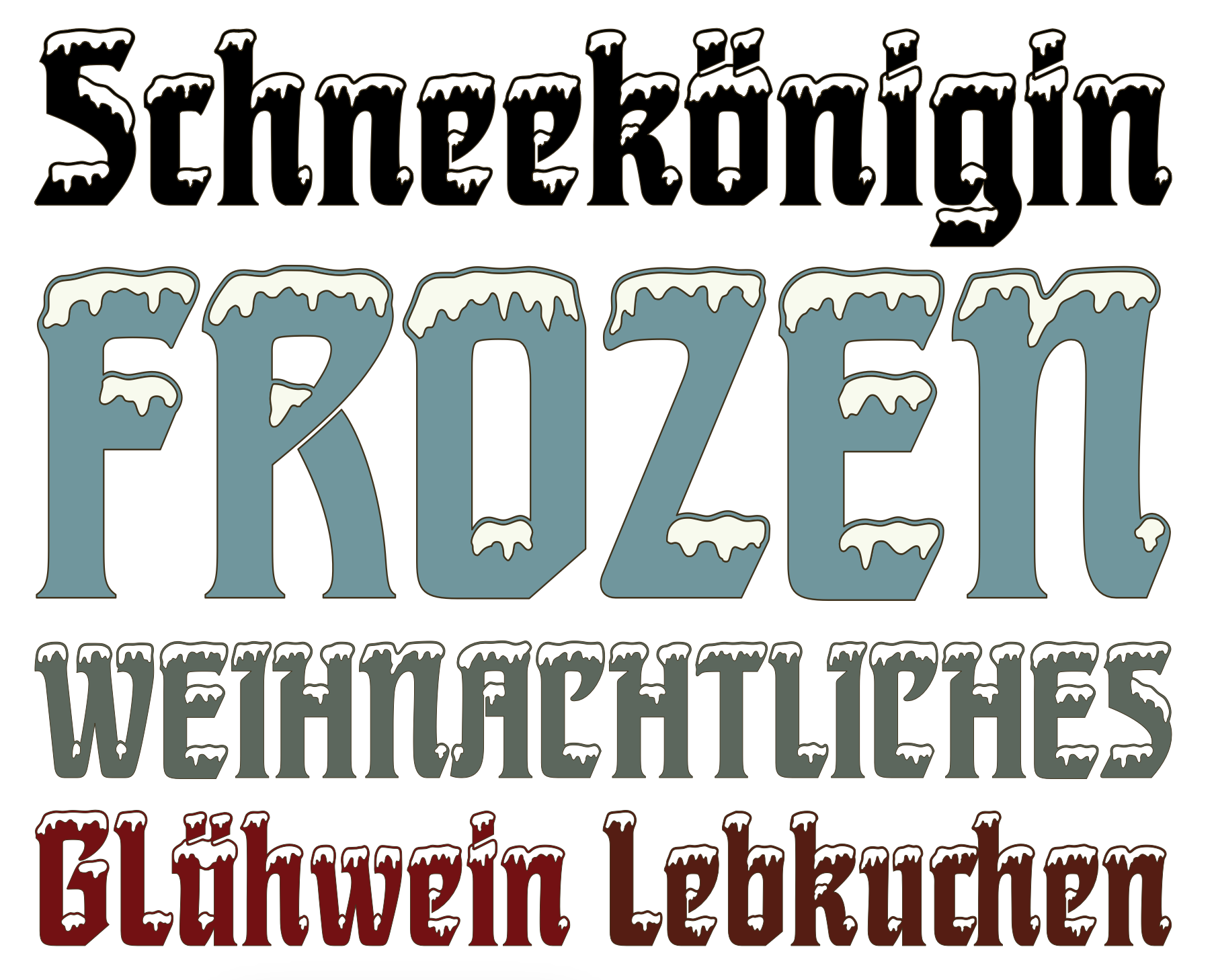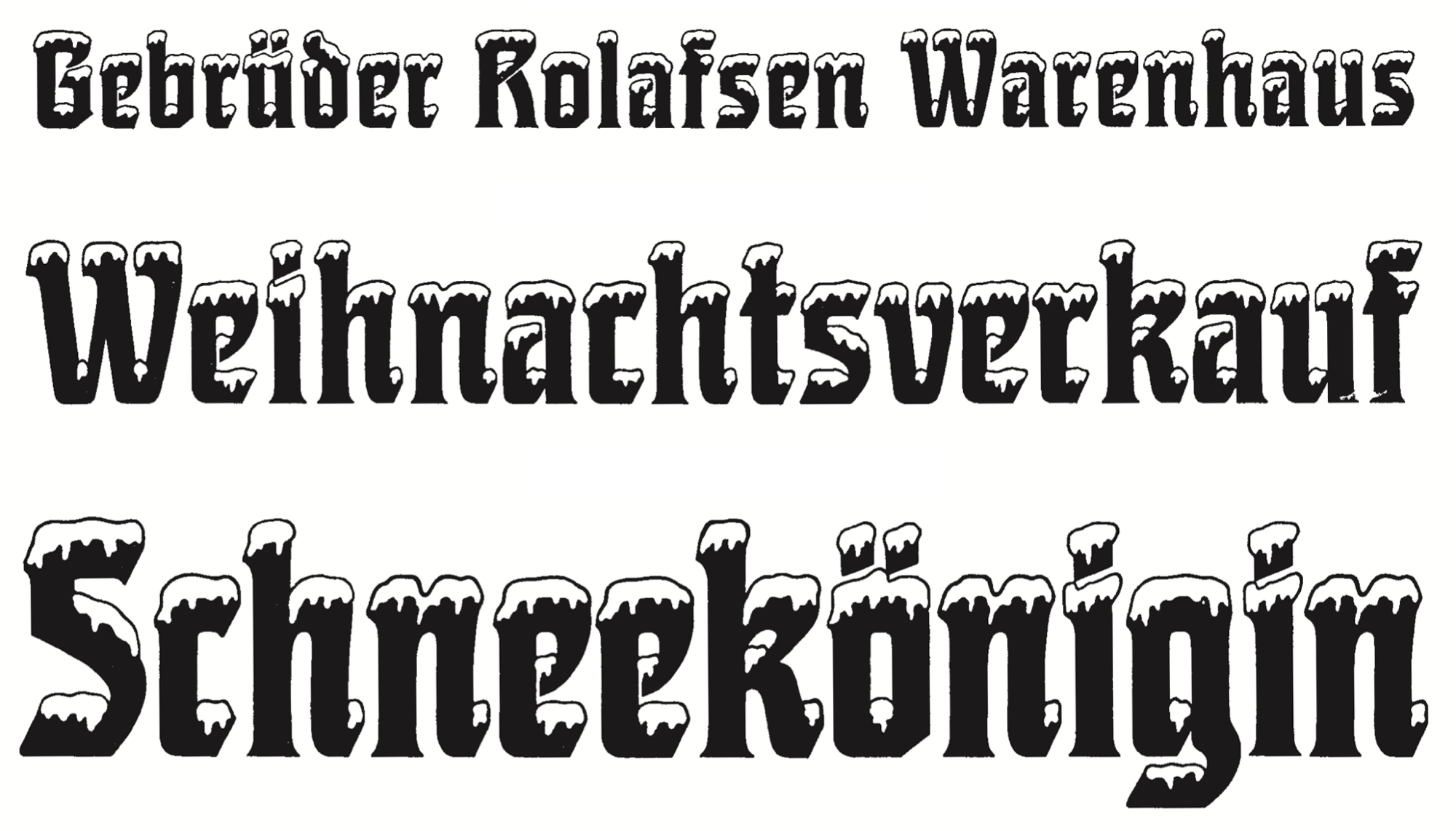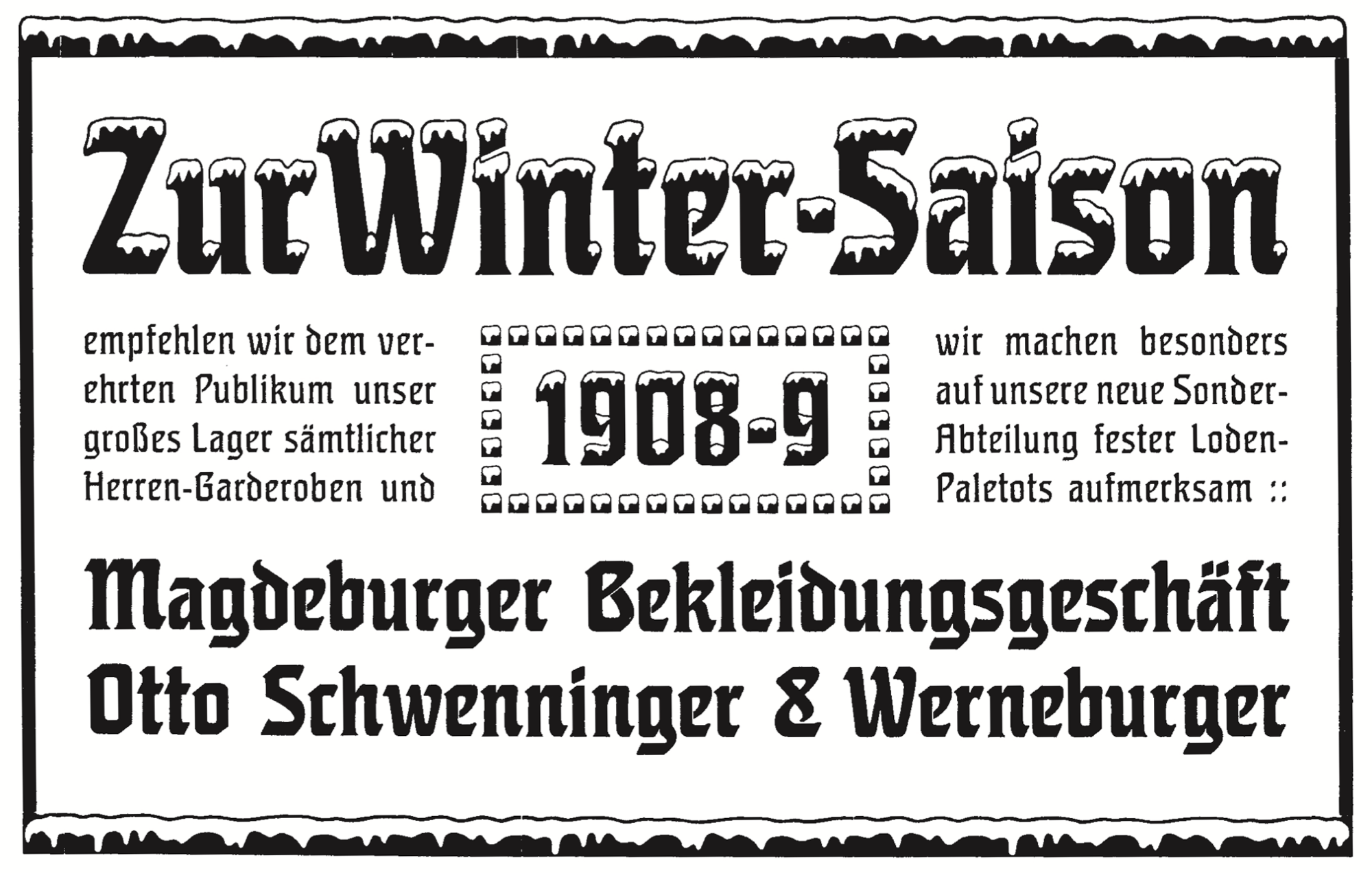
Die Schneekönigin der Gießerei Heinrich Hoffmeister in Leipzig ist eine dekorative Variante der Teutonia fett mit visualisierter Schneebedeckung der Buchstaben. Die Schrift erschien Anfang des 20. Jahrhunderts in einem Schnitt. Wie die Teutonia wurde die Schrift später bei der D. Stempel AG angeboten.
Eine Digitalisierung erschien 2024 als WF Schneekönigin über Walden Fonts. Der Schnee kann dabei wahlweise über einen zusätzlichen Ebenenfont eingefärbt werden.
Bleisatz-Version
WF Schneekönigin